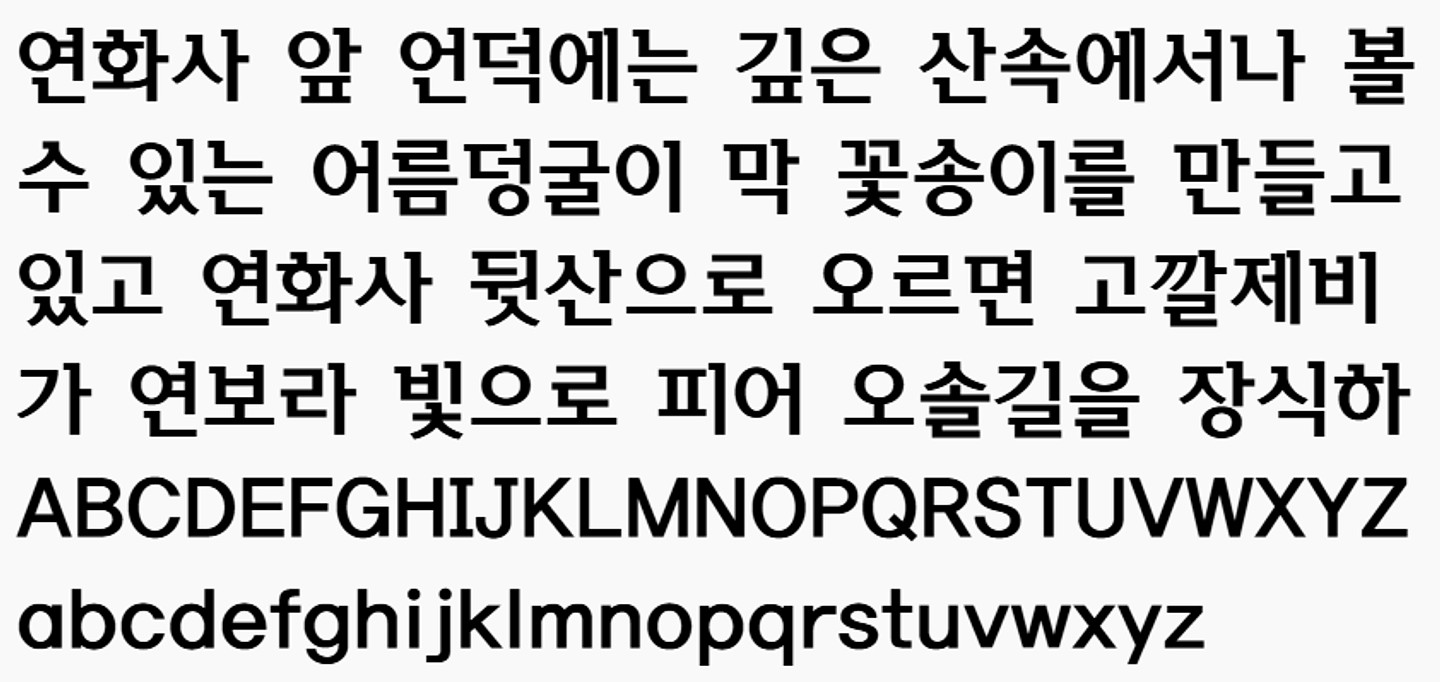
산돌 북 04 Extrabold 폰트인데 혹시 이거랑 최대한 비슷한 무료 폰트 있을까요??ㅠㅠ
이거랑 아주 조금 비슷할 것 같습니다…
210 나무고딕 ExtraBold
a솔향기
a솔향기B 폰트가 산돌북과 딱 닮은 폰트긴 하지만, 비상업용으로만 무료고 상업적 목적 이용 시 라이선스가 필요하다는 제한이 있습니다